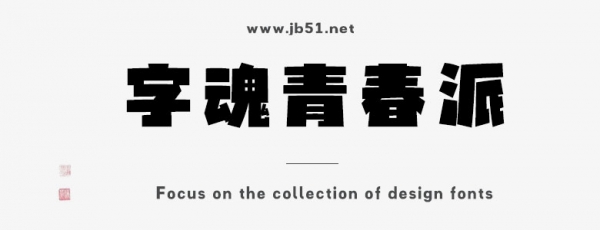
字魂青春派是由字魂字庫推出的藝術(shù)字體,字體筆觸略粗,字體類型偏向黑體,具有活潑、動漫、時尚的風(fēng)格,適合應(yīng)用于藝術(shù)設(shè)計(jì)、平面宣傳設(shè)計(jì)、網(wǎng)頁設(shè)計(jì),書法字帖等領(lǐng)域。
字體背景
字魂青春派字體是由字魂創(chuàng)意字庫設(shè)計(jì)并生產(chǎn)的一款可商用的字體,被收錄于字魂先鋒系列。該字體支持GB-2312標(biāo)準(zhǔn)以及最新的字魂ZH7144標(biāo)準(zhǔn),包含7144個中文、字母、符號和數(shù)字,字體類型偏向黑體,具有活潑、動漫、時尚的風(fēng)格,在市面上廣泛用于旅游、晚會年會、黨政公務(wù)等場景。